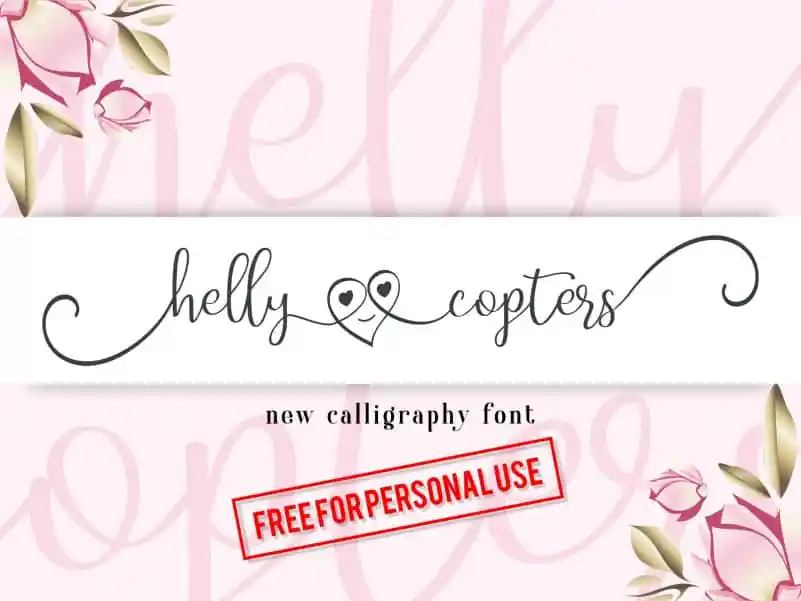
Helly Copters Calligraphy Font – Fonte Grátis
Helly Copters Calligraphy Font
A Helly Copters Calligraphy Font é uma fonte interessante com alternativas únicas e belas. Seu design elegante se destaca entre as muitas opções disponíveis, oferecendo 6 estilos diferentes para escolha. A fonte é perfeita para a criação de convites de casamento, escrever textos românticos, gráfica, logotipos de produtos e muito mais. Seja por sua beleza única ou pelo seu uso versátil na composição de vários tipos de projetos, essa fonte é uma escolha inteligente para quem busca algo novo e especial em suas criações. Não importa o projeto ao qual você deseja aplicar a Helly Copters Calligraphy Font, ela certamente irá chamar atenção e adicionar um toque único aos seus trabalhos.